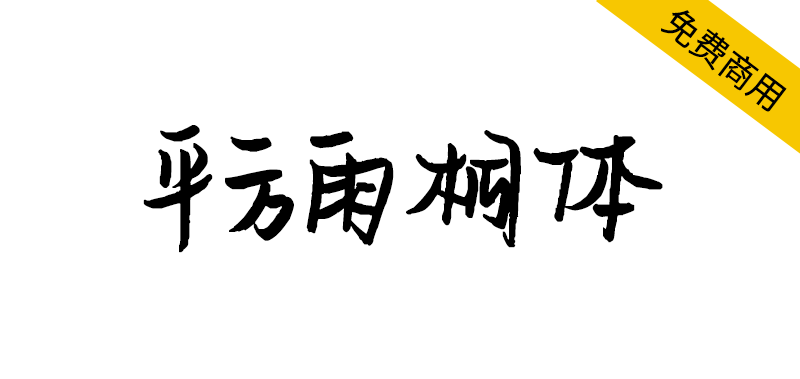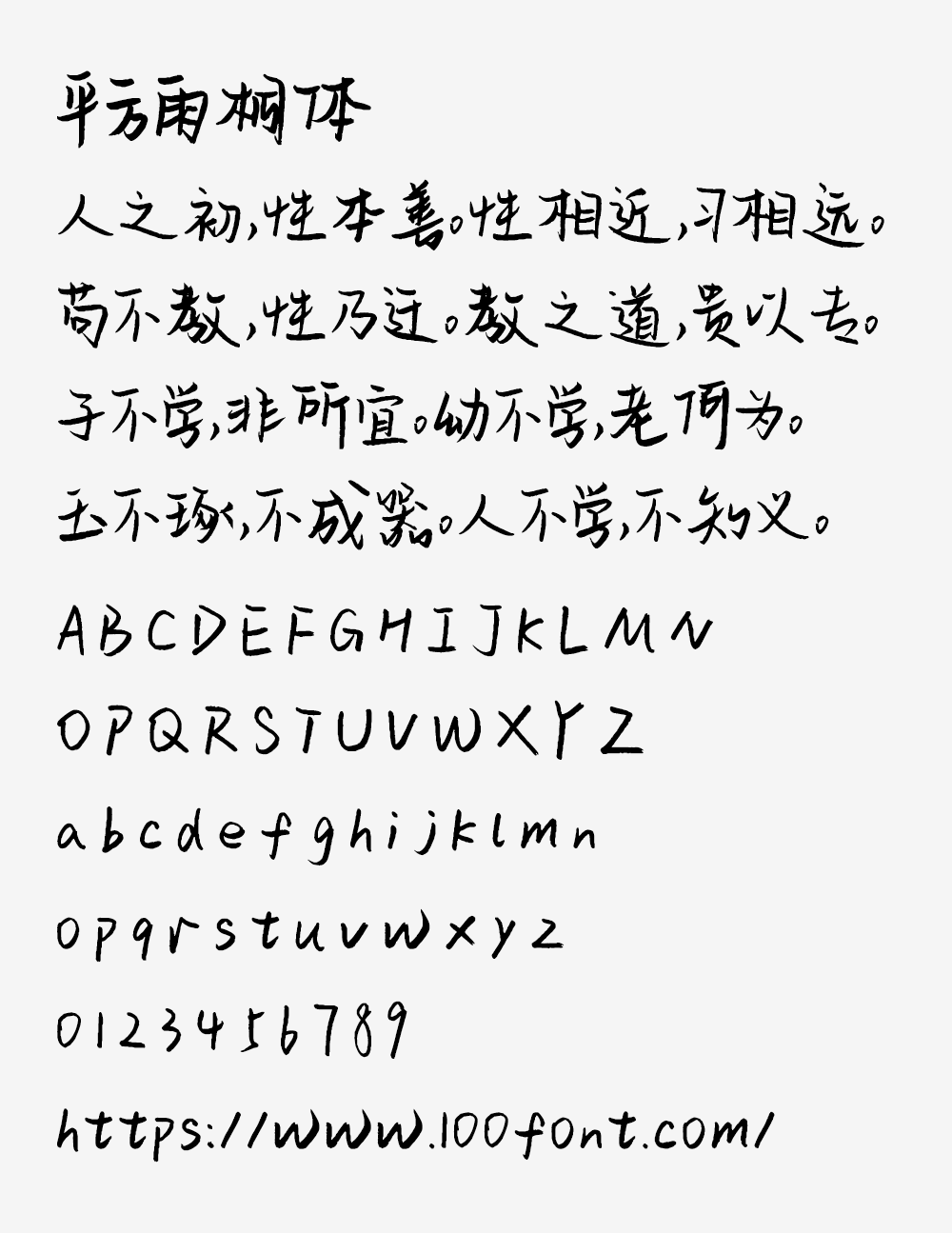
【平方雨桐体】一款字形结构饱满的毛笔手写字体
还在为商用字体授权费发愁?重磅推荐这款可免费商用的“平方雨桐体”!它笔触浑厚有力,字形结构饱满大气,左倾重心设计更添独特韵味。无论是海报标题还是产品包装,都能瞬间提升视觉冲击力,是设计师与内容创作者不容错过的宝藏字体。
【平方雨桐体】一款字形结构饱满的毛笔手写字体
平方雨桐体是一款独具特色的毛笔手写字体,其设计采用左倾重心布局,笔触浑厚有力,字形结构饱满大气,适合用于杂志标题、广告海报、产品包装等领域